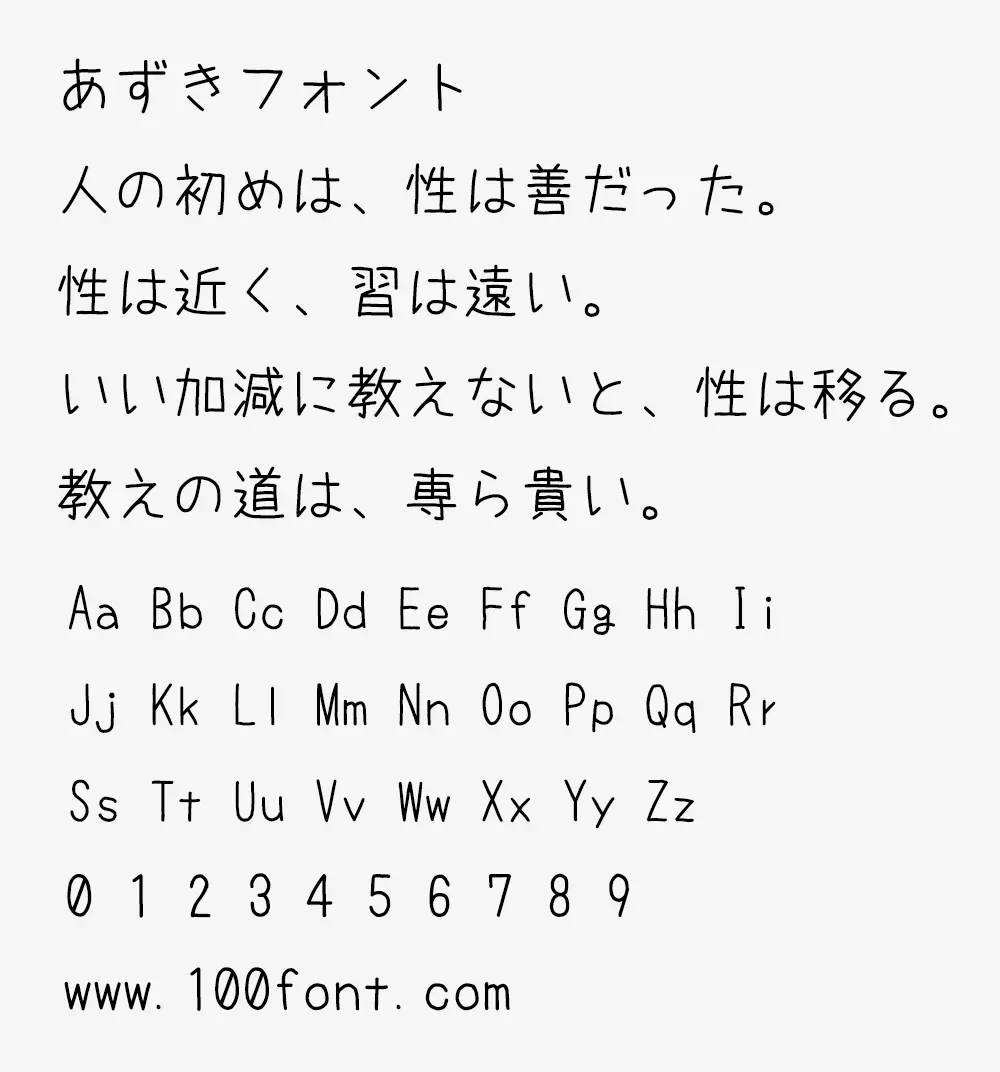
紅豆字體(あずきフォント)這是原始手寫字體,不太嚴肅也不太可愛的字體,建議使用抗鋸齒,它很薄,可能不適合徽標等。
オリジナルの手書きフォントです。
「マジメすぎず、可愛すぎないフォント」
という地味な仕上がりになりました。
アンチエイリアス推奨です。
細い字なのでロゴ等には向いてないかもしれませんが、